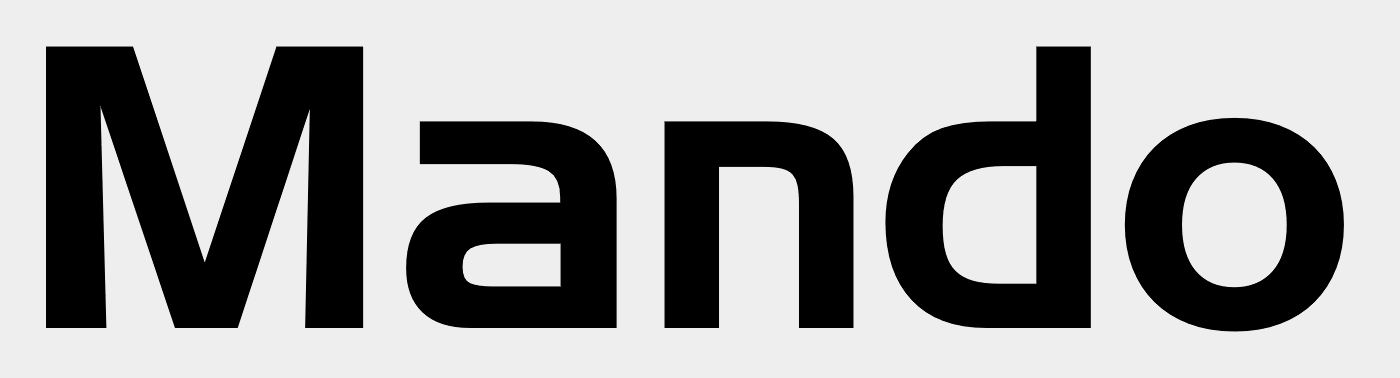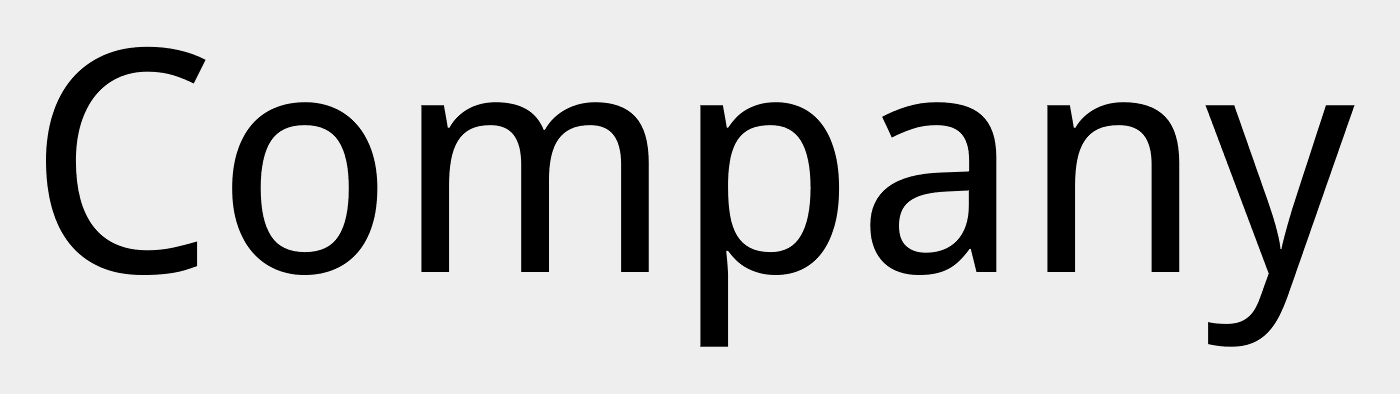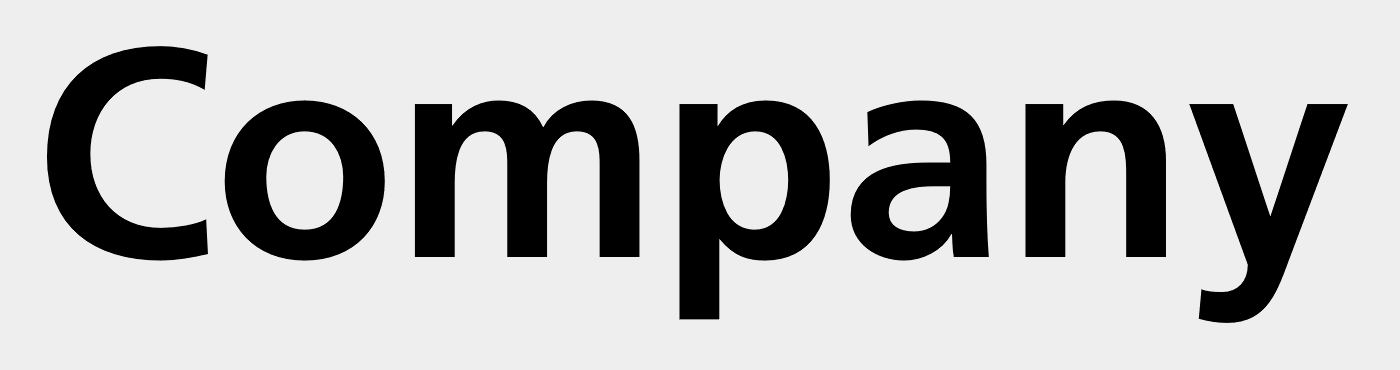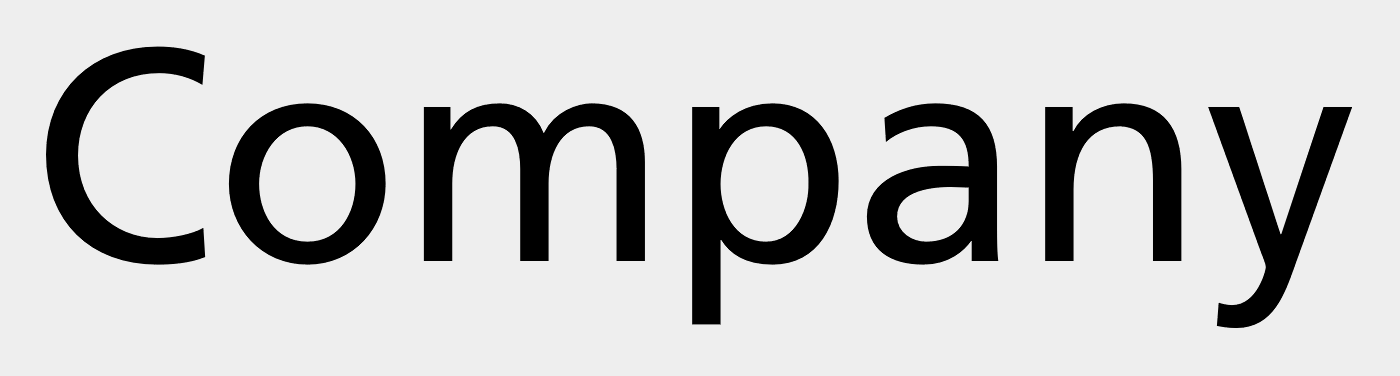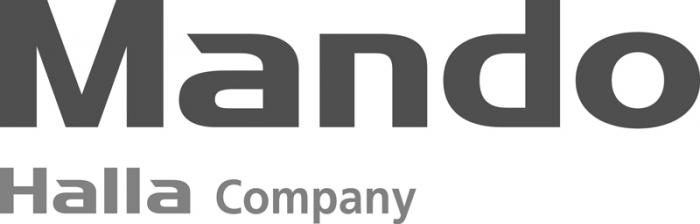
Wie heißen diese beiden Schriften?
das zweite Mal, dass ich Eure Hilfe brauche. Ich habe im Anhang wieder die Schriften gepostet, könnt Ihr mir sagen wie sie heißen? Die Schrift zu "Company" ist mir nicht so wichtig. Aber "Mando" und "Halla" wären mir wichtig zu identifizieren. Hoffentlich basieren die beiden Wörter auf einer Schrift. (Panik krieg)
Das Wort »Company« ist dicht an der Droid Sans dran (Kleinigkeiten stimmen nicht ganz exakt). Die andere Schrift kann ich Dir nicht aus dem Stegreif identifizieren, aber sie sieht mir sehr danach aus, als wäre sie in die Breite gezerrt worden. Schau hier im Font-Wiki und bei den großen Schriftherstellern mal nach dem Stichwort »spornlosen Schriften«, da solltest Du eigentlich fündig werden, sofern es sich um eine Satzschrift handelt.  :-)